20 хипстерских шрифтов, которые придадут вашему сайту народный шарм
Опубликовано: 2017-08-31Хипстер - очень странный и глупый термин. Люди используют его по-разному для разных вещей, но в целом вы можете рассчитывать на то, что он относится к чему-то простому, простому и относящемуся к более простым временам, которые, возможно, когда-либо существовали, а могли и не существовать. Ах да, бороды. Всегда бороды. Славные, славные бороды.
Так что же делает шрифт хипстерским?
Напоминая вам о прошлых годах, о прошлых временах, о работе руками и о том, что вы живете в американской мечте. И снова бороды. Он обязательно должен напоминать вам о бороде.
Шрифтов Hipstery Достаточно для хипстерского клуба
Независимо от того, хотите ли вы, чтобы ваш сайт имел народный шарм или просто имел немного характера, который Google Fonts не может дать вам, существует множество ручных, ретро и старинных шрифтов с нижним правым краем, которые дадут вашим читателям понять, что вы один крутой котик, который раньше был крутым.
Бесплатные хипстерские шрифты
Primitiva Slab
Наш список начинается хорошо: этот шрифт отмечен большинством хипстерских меток: нарисован от руки, хорошо смотрится на текстурированном фоне и обращен назад в самом названии. Хорошая вещь.
Металлургический завод
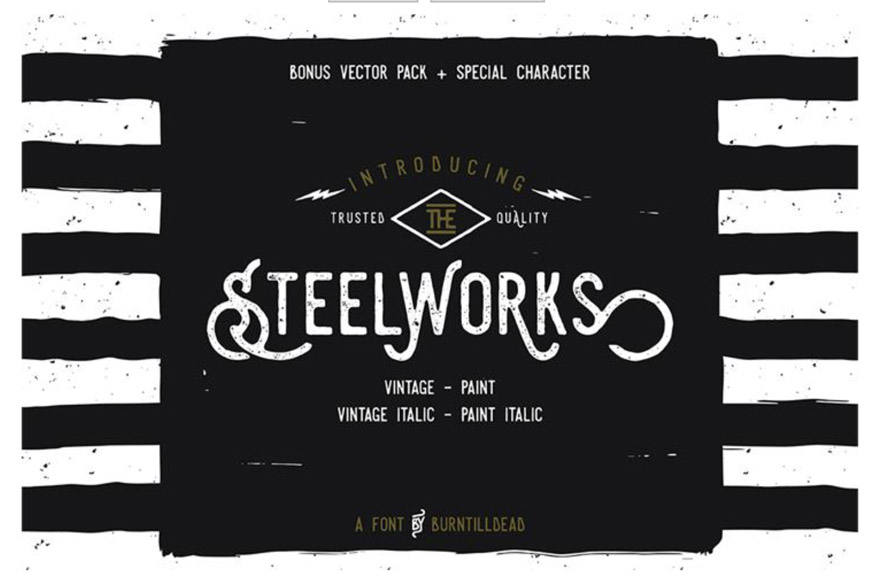
Если вы из тех хипстеров, которые хотят оставаться твердыми, этот шрифт вам подойдет. «Синие воротнички», любящие это, «Сталелитейный завод» обладает векторной графикой и курсивом, а также тщательно продуманными небрежными мазками. Плюс на логотипе есть молния, и это просто круто.
Авентура
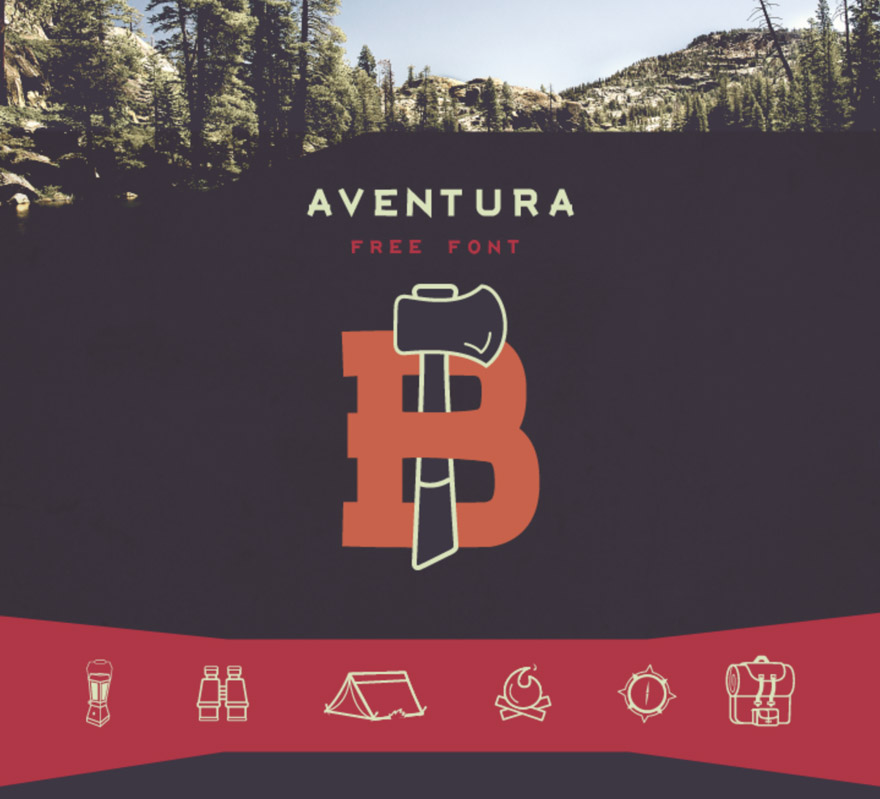
Думаю, ничто не говорит о хипстере так, как отдых на свежем воздухе. Хипстеры любят приключения. Этот шрифт олицетворяет любовь ко всему естественному, лесному и топорному. То есть на логотипе есть топор. Это довольно рискованно.
Воскресенье
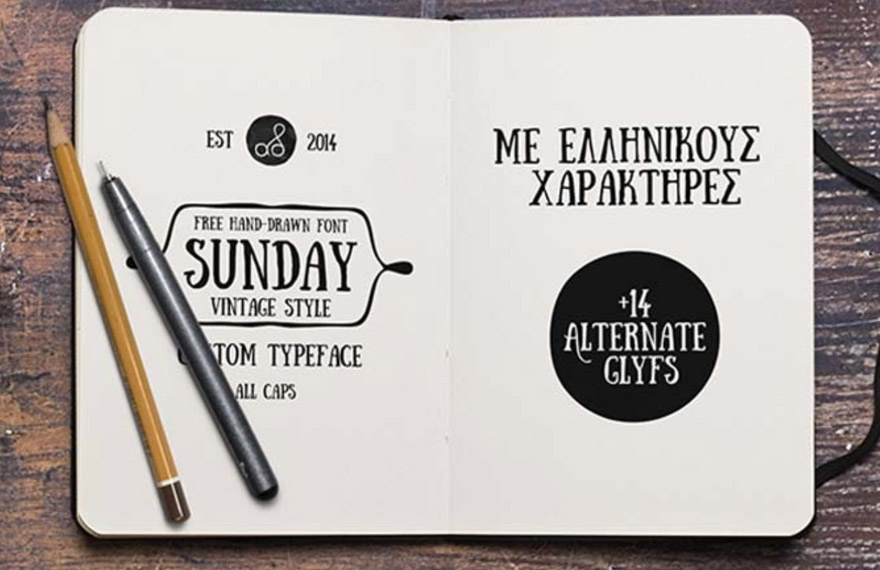
Знаете, что говорят о воскресеньях? Веселый день! Ха! Шрифт каламбуры рок. Прямо как этот шрифт. Это непринужденно, но в нем есть нотка формальности. Идеально подходит для блога с идеями, который у вас есть, или даже для сайта электронной коммерции, где вы продаете сшитые вручную блокноты и футболки с трафаретной печатью.
Кость Че
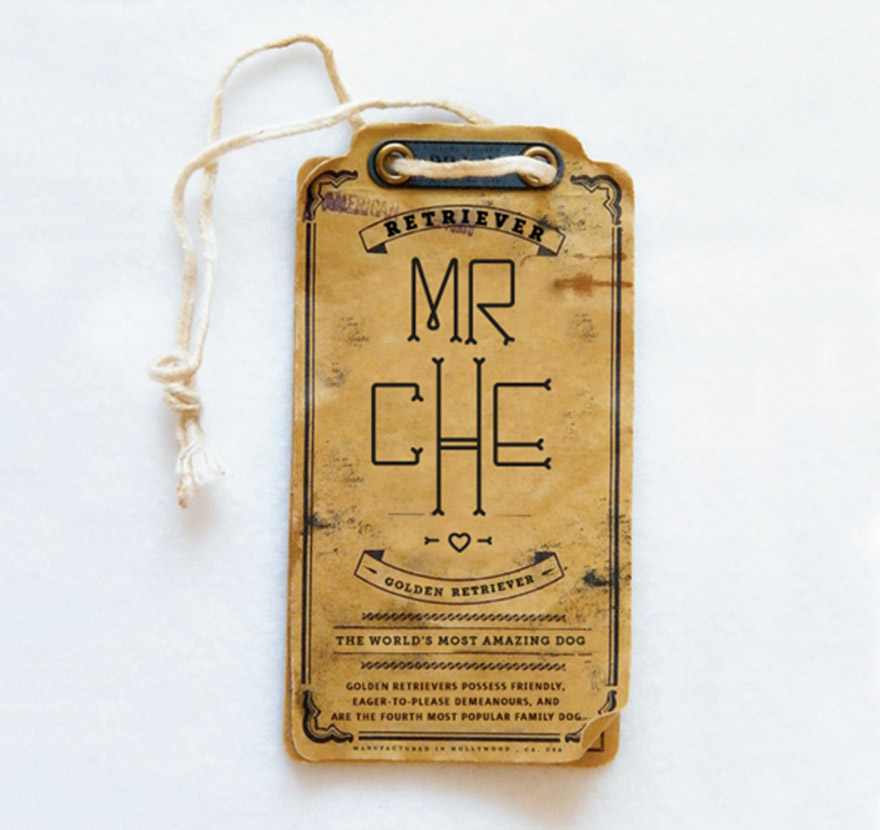
Вы должны оценить шрифт, сделанный для собаки дизайнера. Ничто из того, что я напишу об этом шрифте, не будет лучше, чем сам дизайнер: «Моя собака любит кости. Я экспериментировал с этим шрифтом для Че и других любителей собак. Имеет округлые края и уплотненные узкие формы. Угол каждой буквы имеет форму кости, которая является любимой частью Че ».
Милыйпанк
Мы привыкли к панку, эмо-панку, киберпанку, стимпанку, но милый панк? На самом деле, вписывается. Противостояние истеблишменту - вот в чем суть панка, и этот хипстерский шрифт делает именно это. Не суровый, не слишком модный и не чрезмерно причудливый, возьмите этот и скажите этим строгим шрифтам без шрифтов, что вы больше не собираетесь его выносить!
Лента
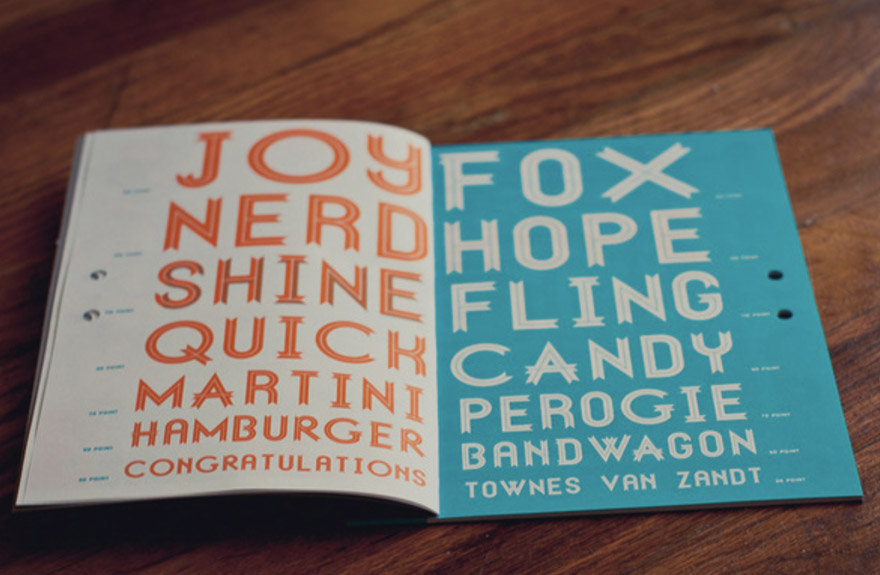
Совершенно противоположно нашей последней записи, у нас есть шрифт, который очень удачно назван именно так, как он есть. Похоже на ленточку. Причудливый и стильный, вы не можете не думать о своем детстве и об упаковке ваших любимых игрушек, когда видите это. По крайней мере, я не могу.
Мегаполис
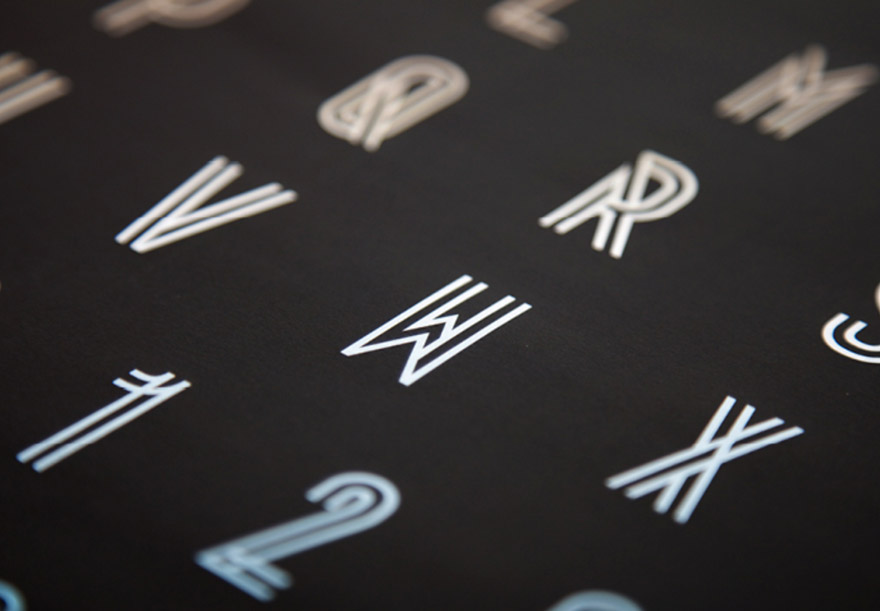
Ничто так не говорит о хипстере, как возвращение к одному из самых первых полнометражных научно-фантастических фильмов. Если вы хотите, чтобы люди знали, что вы цените дни славы, позвольте им увидеть ваше анахроничное уважение к будущему и прошлому. И роботы. Все любят роботов.
Салливан
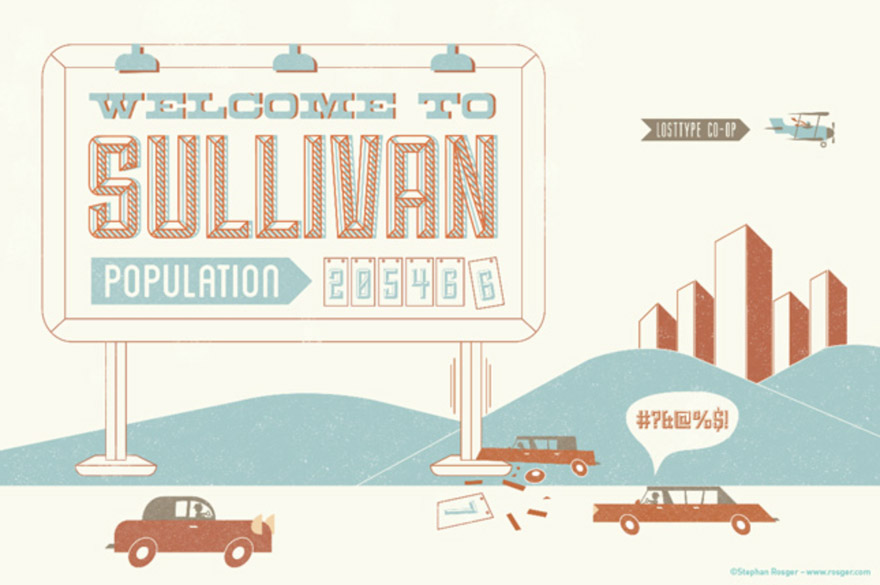
Прямо из старых добрых времен Салливан похож на американскую мечту. Жуткий и чистый шрифт заставит ваших посетителей чувствовать себя комфортно и желанно. Так что приходите, платите сколько хотите и наслаждайтесь содовой или пивом.
Флоренция
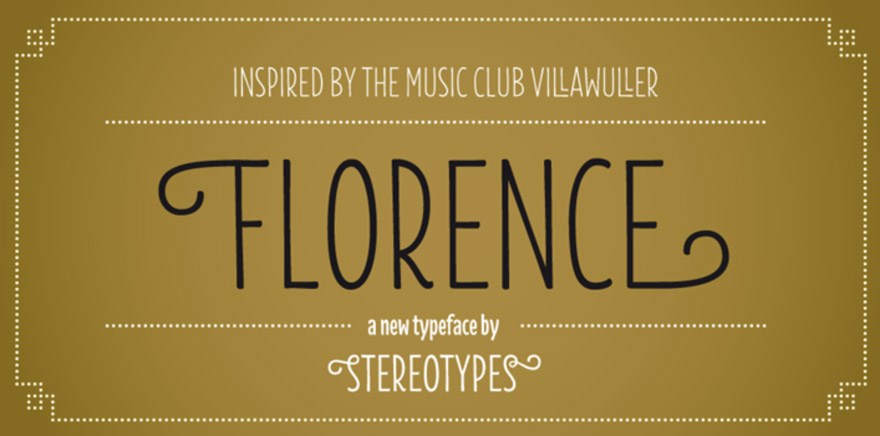
Хорошо, буду честен: я включил этот шрифт, потому что он заставил меня хихикать. Это название моего города, в котором удивительно много хипстеров, которые постоянно меняются местными кафе, коворкингами и фермерскими рынками. Если бы я шутил. Помимо моих личных шуток, Florence - это совершенно красивый шрифт, который придаст винтажный, стильный вид любому сайту, на котором вы его разместите. Особенно, если вы управляете кафе, коворкингом или фермерским рынком.
Кварц 974 светлый
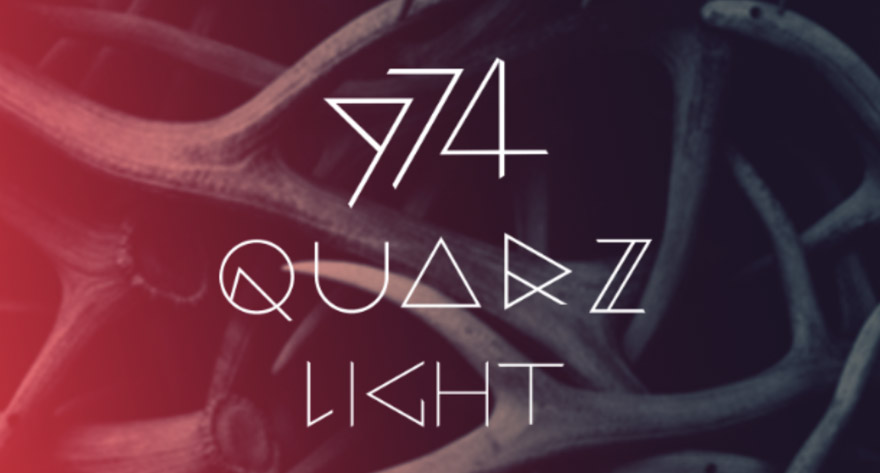
Мне просто нравится название этого шрифта. Насколько хипстеры любят треугольники. До недавнего времени я не знал, что это так, но чем больше я читал, тем больше хипстерский дизайн сочетал в себе строгие геометрические узоры с естественными пейзажами и фотографиями. Неудивительно, что он абсолютно великолепен и лично стал одним из моих любимых стилей. И этот шрифт бесплатный и идеально подходит для того странного сопоставления, о котором вы, возможно, не думали раньше. Пожалуйста.
Регина Блэк
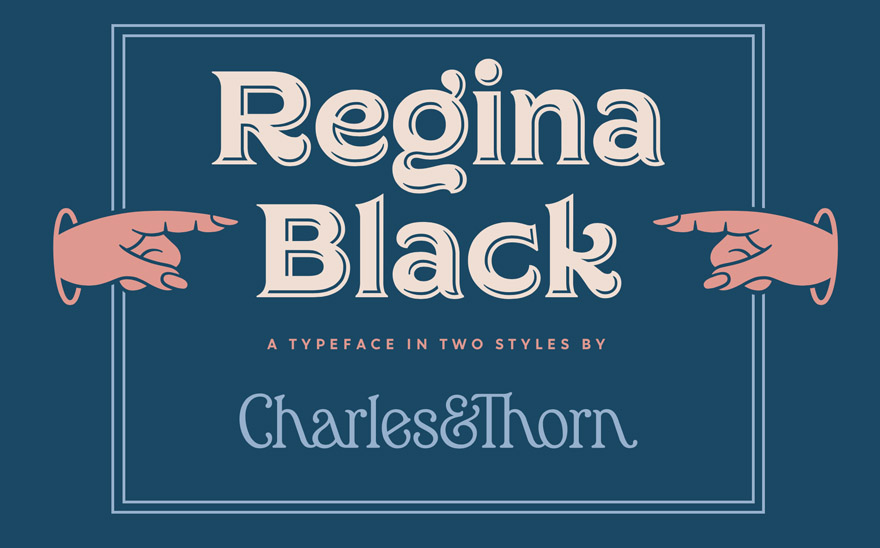
Опять же, я просто позволю веб-сайту шрифта говорить сам за себя: «Regina Black имеет тяжелые формы букв, на которые в равной степени влияют элегантный дизайн начала 1900-х годов и короткие дружелюбные шрифты, популяризированные в 1970-х годах. Дружелюбный, встречайте фанки ».